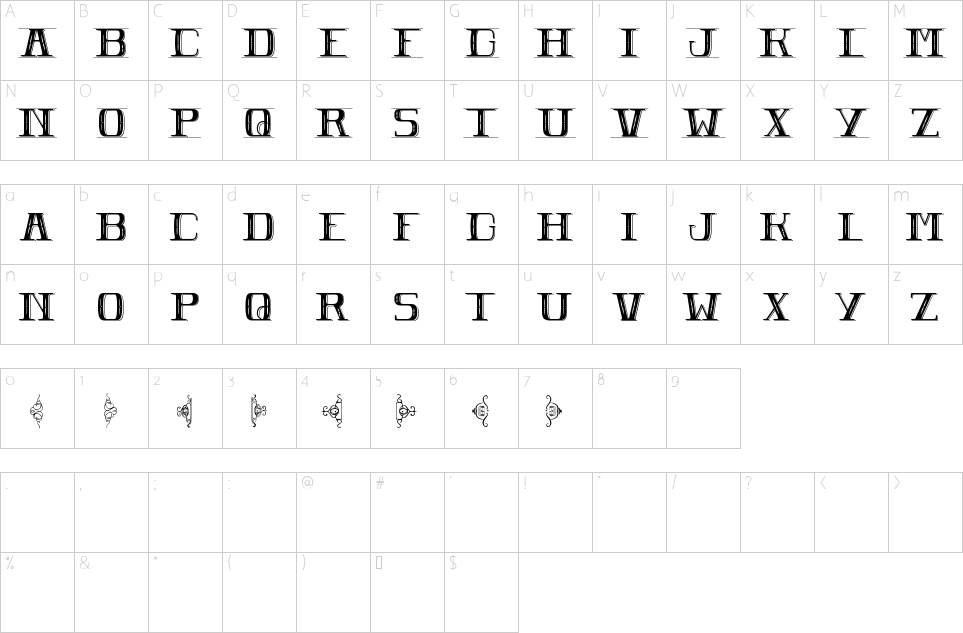
A fonte Pomerole oferece um ar elegante e sofisticado, perfeita para criar designs gráficos distintos. Ela foi projetada por Maelle Keita e já foi baixada mais de 17.200 vezes. Esta fonte é uma escolha ideal para designers que buscam um estilo único para seus projetos digitais. Seja para websites, banners, design gráfico, ou mesmo para criações de software, a Pomerole adquire um toque de sofisticação e personalidade. Se você está procurando por uma fonte de qualidade que ainda é gratuita, Pomerole é definitivamente um nome a ser considerado. Download Pomerole e deixe sua criação brilhar com esta font elegante.